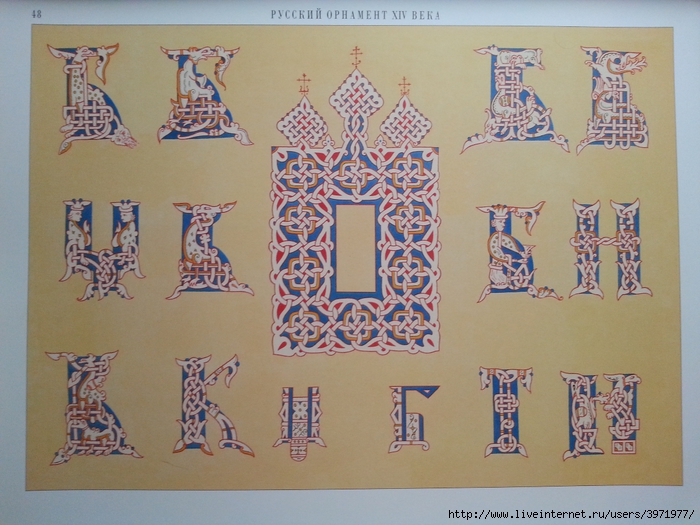
История русского шрифта презентация, доклад
История русского шрифта
Древнерусскими называют все рукописные и первопечатные шрифты со времени их возникновения и вплоть до образования новой графики гражданского письма и гражданского шрифта ( конец XVII- начало XVIII века).
Древнерусские шрифты
Глаголическая азбука
Книги на Русь пришли с официальным принятием христианства в 988 году. Наряду с кириллицей существовала другая азбука — глаголическая. Глаголические буквы в полном их составе не имели сходства ни с одной из известных азбук. Она включала в себя черты, петли, овалы и полуовалы.
На Руси глаголица продержалась не долго и в конце концов была полностью вытеснена кирилловским письмом.
В середине IX века святые братья Кирилл и Мефодий уроженцы г.
Солуни (Солоники) в Македонии разработали для западных славян азбуку и перевели на славянский язык ряд богослужебных книг.
Заслуга Кирилла состоит в том, что он впервые создал азбуку с четкой и ясной графикой знаков, положив в основу греческое унциальное письмо и дополнив его буквами, обозначавшими специфический звуки славянского языка (шипящие, свистящие и йотированные).
Он расставил буквы в определенной последовательности, предав им и цифровое значение. Буквами кириллицы в течение многих веков обозначались простые и многозначные цифры.
С помощью изобретенной им азбуки Кирилл сделал первый перевод Библии на славянский язык.
Новая азбука, передававшая все особенности живой речи, очень скоро получила широчайшее распространение не только в церковнославянских книгах, но и в светском, деловом и обычном письме.
В истории древнерусского шрифта выделяют основные каллиграфические варианты кириллицы:
— с XI века — уставное письмо;
— с XIV века — полуустав, послуживший образцом для первопечатного шрифта в середине XVI века; в начале XV века получают распространение различные виды скорописи;
— с XV века декоративное письмо — вязь;
Устав — ранняя каллиграфическая форма кириллицы. Буквы устава имели почти квадратные пропорции и отличались прямолинейностью и угловатостью форм.
У С Т А В
— В строке буквы расставлялись свободно, промежутков между словами не было.
— Расстояние между строками равно корпусу буквы или несколько больше , знаки -широкого, жирного (в стойках) начертания, за исключением нескольких узких закругленных букв ( О, Е, С, Р). Буквы З, У, Р, Х, Ц, Щ имели сильные выносные элементы, которые несколько оживляли монотонность всего письма.
— Угол наклона пера менялся в процессе письма и зависел от формы буквы.
Текст, выполненный полууставом, имеет более светлую общую картину, буквы округлее и мельче, слова и предложения разделены четкими промежутками. Появляется целая система знаков препинания.
П О Л У У С Т А В
— Начертание более простое, пластичное и быстрое, чем в уставном письме.
— Контраст штрихов меньше, перо затачивается острее.
— Под влиянием стабилизировавшегося положения пера улучшилась ритмичность строк.
— Письмо приобретает заметный наклон.
— Засечки встречаются редко, концевые элементы у ряда букв оформляются штрихами, по толщине равными основным.
— Полуустав послужил основой для шрифтов первопечатных книг.
Киевская Псалтирь (РНБ. ОЛДП.
F 6)
Разворот рукописного Месяцеслова. Конец XVIII — начало XIX века.
Скоропись
Грамоты, акты, книги уже с XIV века стали писать скорописью. Скоропись оказалась одним из самых подвижных видов кириллического письма.
С К О Р О П И С Ь
В XVII веке скоропись, отличаясь особой каллиграфичностью и изяществом, превратилась в самостоятельный тип письма с присущими ему чертами: округлостью букв, плавностью их начертания, а главное, способностью к дальнейшему развитию. Именно в скорописи, близкой к обычному письму, могла развиваться минускульная форма. Уже в конце XVII века образовались такие формы букв а, б, в, е, з, и, т, о, с, которые и в дальнейшем почти не претерпели изменений.
Скоропись XV века
Вязь — особый декоративный вид письма, связывающий строку в один непрерывный орнамент в стиле арабесок( вид орнамента).
В Я З Ь
Различают два вида вязи: круглую и угловатую (штамбованную).
В русских рукописях преимущественно развивалась штамбованная (угловая) вязь. Один из основных приемов вязи — мачтовая лигатура, в которой два соседних штриха (штамба) двух соседних букв превращались в один. Пустоты, образующиеся при этом, заполнялись либо сильно овальными или мендалевидными формами букв О, Е, С, или полумачтами соседних букв, а иногда декоративными элементами.
Выполненные золотом или киноварью, они несли особую художественно — декоративную нагрузку в различных памятниках письменности.
Псковский Златоуст 16 в.
Максим Грек, 1587 («сия словеса сотворил есть инок»)
Самой ранней точно датированной книгой является написанное на пергамене кириллицей «Остромирово Евангелие» (1056-1057).
Книга написана дьяконом Григорием за 8 месяцев и является шедевром искусства книги Древней Руси, иллюстрированная изображениями евангелистов, великолепными заставками и инициалами, в которых творчески усваивались византийские традиции.